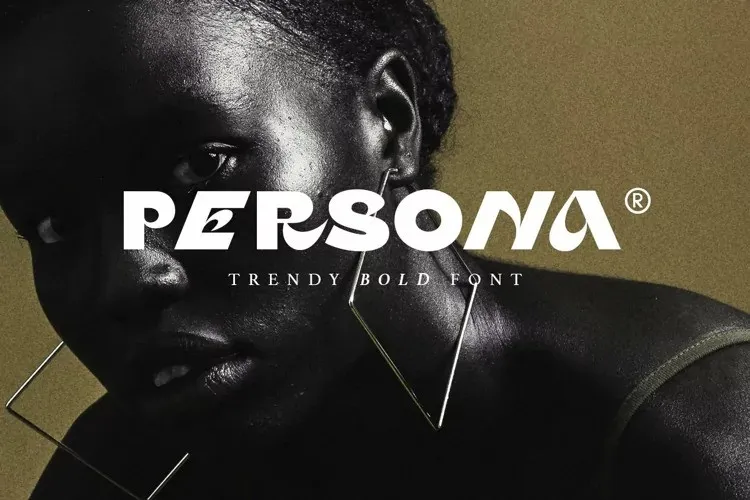
Essa é uma fonte de display inspirada na vinheta vintage que traz uma aparência única. A Persona Font contém letras maiúsculas e minúsculas com diferentes formas, permitindo você usar as duas no mesmo texto, tornando-o mais chamativo. Além disso, o melhor da fonte é a versão itálica como alternativas, fazendo com que possa combinar tudo sem preocupações sobre a kerning! Esta é uma fonte perfeita para uso em revistas, panos de papel e ideal para headlines. A Persona Font também suporta múltiplas línguas. É uma excelente escolha para aqueles procurando por um estilo retro moderno que oferece o poder da personalização sem a complexidade do ajuste de espaçamento.